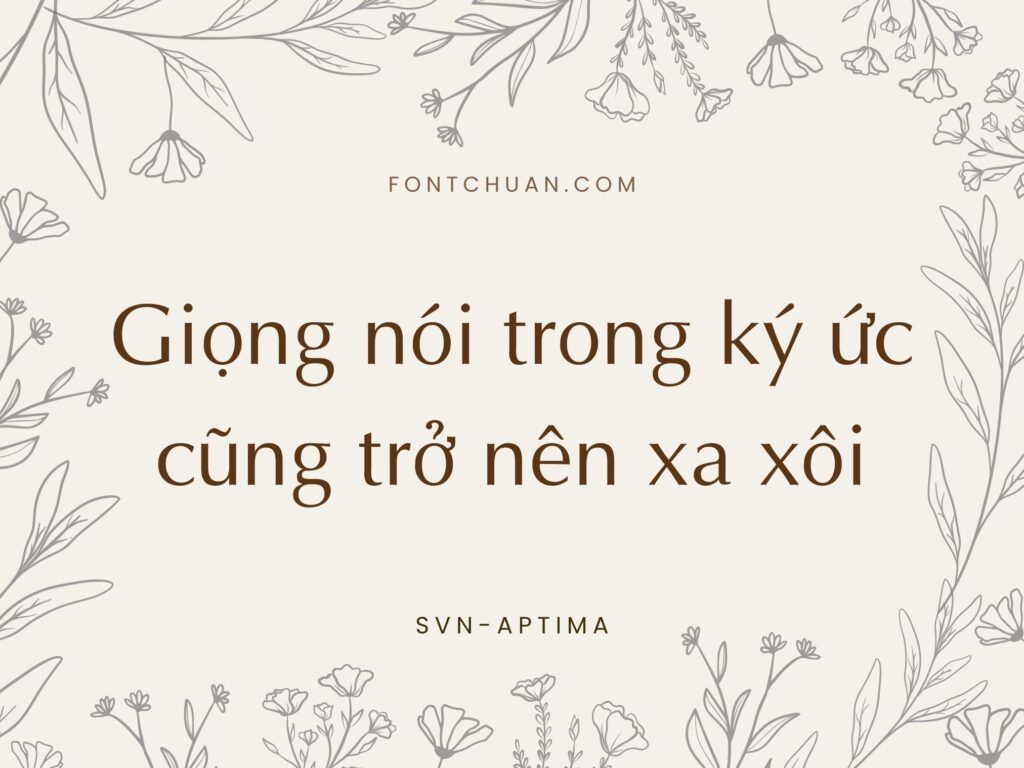
Font SVN Aptima Việt Hóa
Font SVN Aptima là phiên bản Việt hóa của kiểu chữ Aptima, được thực hiện bởi Styleno.1 Fonts. Aptima là một kiểu chữ sans-serif hiện đại, nổi bật với các đường nét mềm mại và cân đối, tạo cảm giác chuyên nghiệp và dễ đọc. Font này thích hợp cho nhiều mục đích sử dụng khác nhau, từ văn bản nội dung đến tiêu đề và thiết kế đồ họa.
SVN Aptima lý tưởng cho các dự án thiết kế logo, tiêu đề, bao bì sản phẩm và các ấn phẩm quảng cáo. Các ngành nghề như quảng cáo, giáo dục và công nghệ có thể tận dụng font này để tạo điểm nhấn trong thiết kế. Ngoài ra, font cũng thích hợp cho các sự kiện như Tết, Giáng sinh, Valentine và các lễ hội khác.